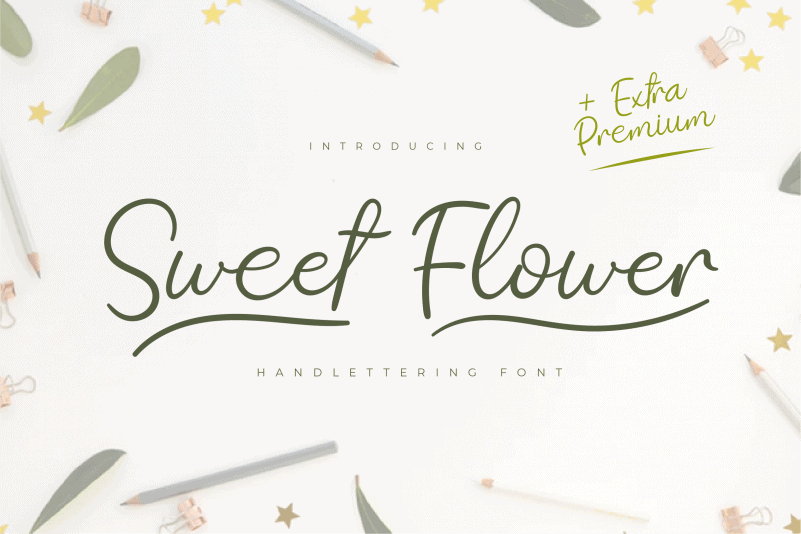
Sweet Flower Script Font – Fonte Grátis
Sweet Flower Script Font
A Sweet Flower Script Font é uma elegante escolha para quem busca uma fonte com traços suaves e fluidos. Ela oferece caracteres bonitos e equilibrados, tornando-a perfeita para adicionar a diversos projetos criativos. Esta fonte se destaca por sua delicadeza e sofisticação, criando um impacto atraente em qualquer design. Seja para editoriais de moda ou arte digital, essa fonte irá enriquecer seus trabalhos de forma elegante e única, tornando-os ainda mais memoráveis. Adicionar Sweet Flower Script à sua paleta de fontes certamente eleva suas ideias criativas a um nível superior.